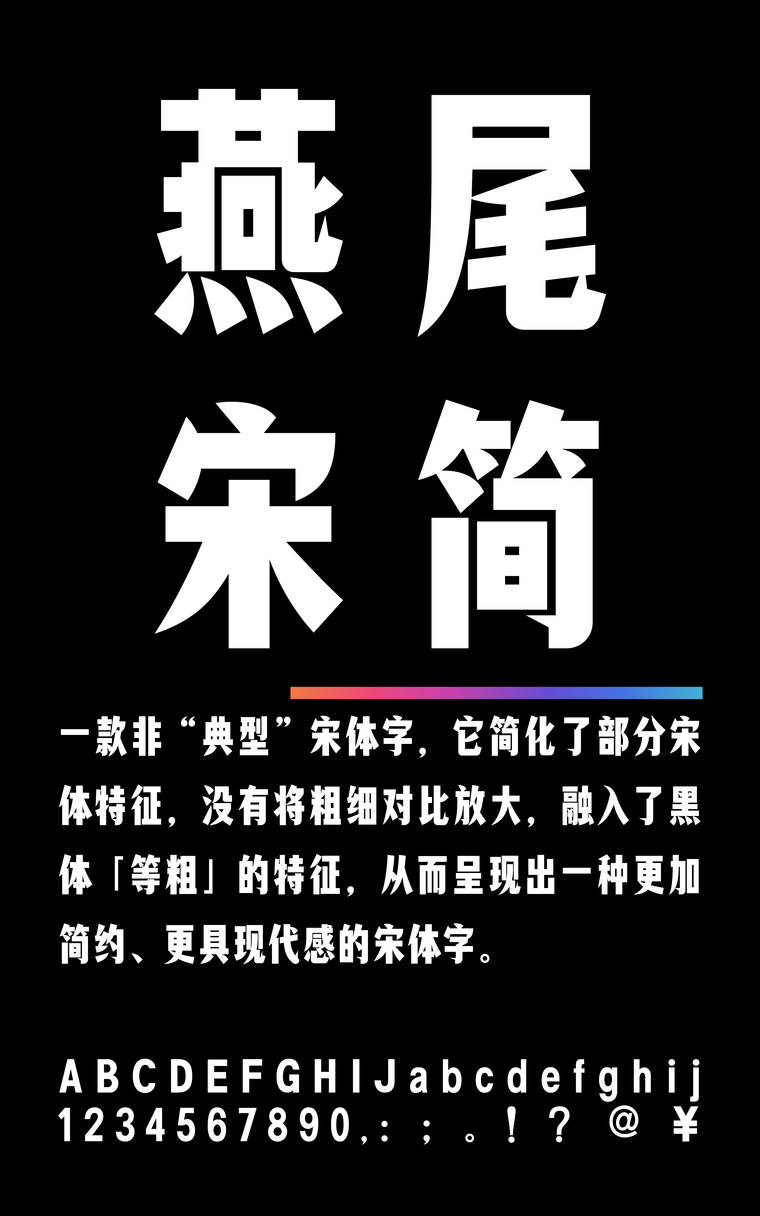
锐字潮牌燕尾宋简 超粗
锐字潮牌燕尾宋简 超粗,这款字体结构工整、笔画清晰,兼顾美观与易读性,适用于标题、正文、海报、包装、LOGO 等多种场景。字形优雅稳定,风格百搭耐看,适配日常排版与创意设计,让文字呈现更舒适、更具质感。锐字潮牌燕尾宋简 超粗一笔一画,皆是细节,以均衡的比例、流畅的线条打造舒适视觉体验,字形端正大气,风格简约现代。无论是商业设计、品牌宣传还是日常排版,都能轻松驾驭,让文字更有格调与力量。锐字潮牌燕尾宋简 超粗字体下载。
锐字潮牌燕尾宋简 超粗字体介绍
锐字潮牌燕尾宋简 超粗字样展示
锐字潮牌燕尾宋简,一款非“典型”宋体字,它简化了部分宋体特征,没有将粗细对比放大,融入了黑体「等粗」的特征,从而呈现出一种更加简约、更具现代感的宋体字。最具特色的是锋利如剪刀一般的“燕尾”收笔,轻盈、翩跹,引发人们对这个字体的无限遐想与探索。